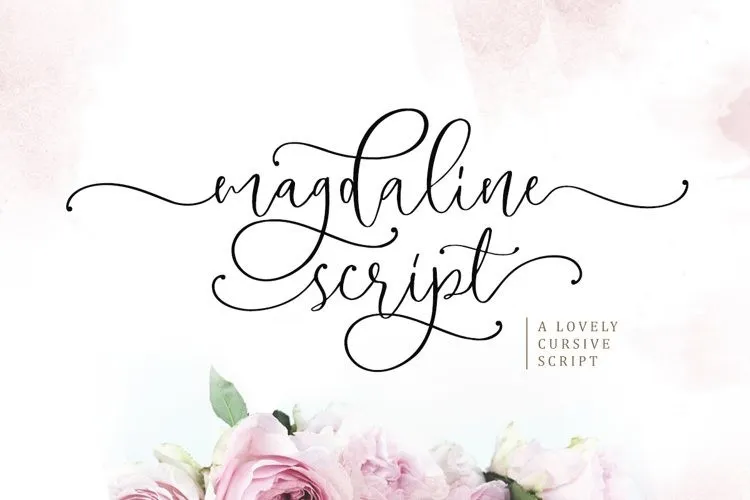
Magdaline Calligraphy Font – Download Grátis
A Fonte Magdaline é uma criação moderna da Saridezra que oferece uma mistura autêntica e casual para quem busca estilos criativos no design digital. Esta fonte foi projetada para se destacar com detalhes sofisticados, incluindo ligaturas duplas, swashes de inicial e terminal, além de alternativas especiais para atender a um vasto número de necessidades de criação de design. Com o seu PUA Encoded já pronto, é uma escolha perfeita tanto para criar logos que representem sua marca, como para projetos de moda sofisticada ou para invitations de casamento elegantes e citações escritas à mão. Essa fonte se destaca não só por sua beleza e versatilidade mas também pela capacidade de personalizar seus projetos de design com facilidade, tornando-a uma opção valiosa para designers amadores e profissionais. Não espere mais: explore a Magdaline Calligraphy Font agora!